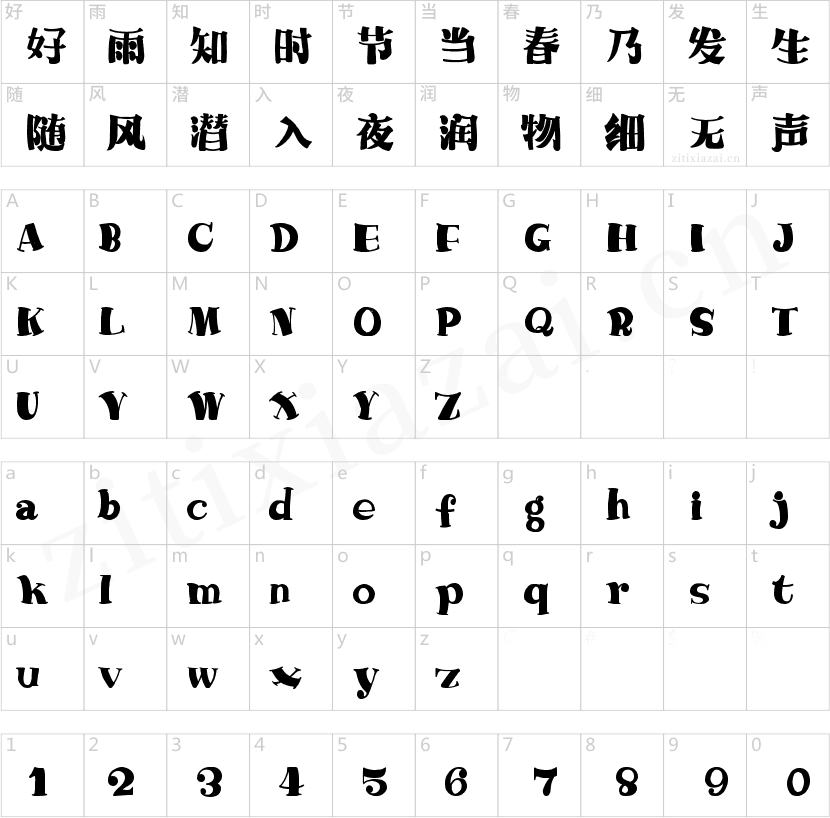
字魂222号-萌趣哈哈宋
字魂222号-萌趣哈哈宋,这款字体结构工整、笔画清晰,兼顾美观与易读性,适用于标题、正文、海报、包装、LOGO 等多种场景。字形优雅稳定,风格百搭耐看,适配日常排版与创意设计,让文字呈现更舒适、更具质感。字魂222号-萌趣哈哈宋一笔一画,皆是细节,以均衡的比例、流畅的线条打造舒适视觉体验,字形端正大气,风格简约现代。无论是商业设计、品牌宣传还是日常排版,都能轻松驾驭,让文字更有格调与力量。字魂222号-萌趣哈哈宋字体下载。
字魂字体字小魂萌趣哈哈宋字体是由字魂创意字库设计并生产的一款可商用的字体,被收录于字小魂系列。该字体支持GB-2312标准,包含6774个中文、字母、符号和数字,字体类型偏向创意字体,具有力量、活泼的风格,在市面上广泛用于印刷品&包装、餐饮食品、海报企宣等场景。